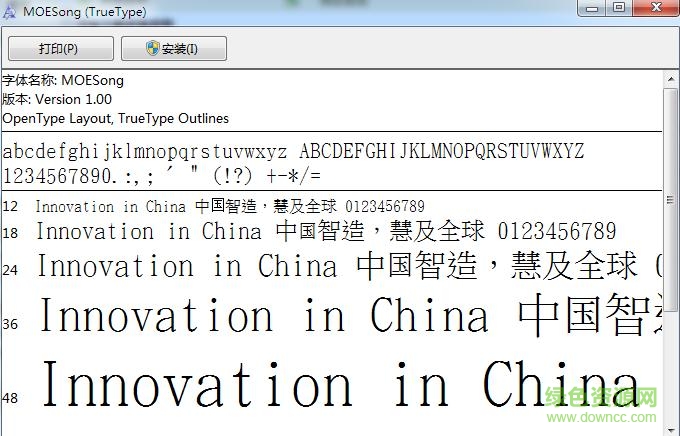
臺灣標(biāo)準(zhǔn)宋體是一款繁體宋體中文字體,字體較為瘦長,擁有楷體的筆型,各筆劃等粗,整體看上去工整、大氣,有需要的朋友歡迎免費(fèi)下載!
臺灣教育部標(biāo)準(zhǔn)宋體是一款臺灣地區(qū)使用的宋體字體,字身修長,工整秀麗,勻稱,筆畫挺拔,起落偏頓,橫斜豎直,粗細(xì)一樣,間隔均勻,常用于印刷。